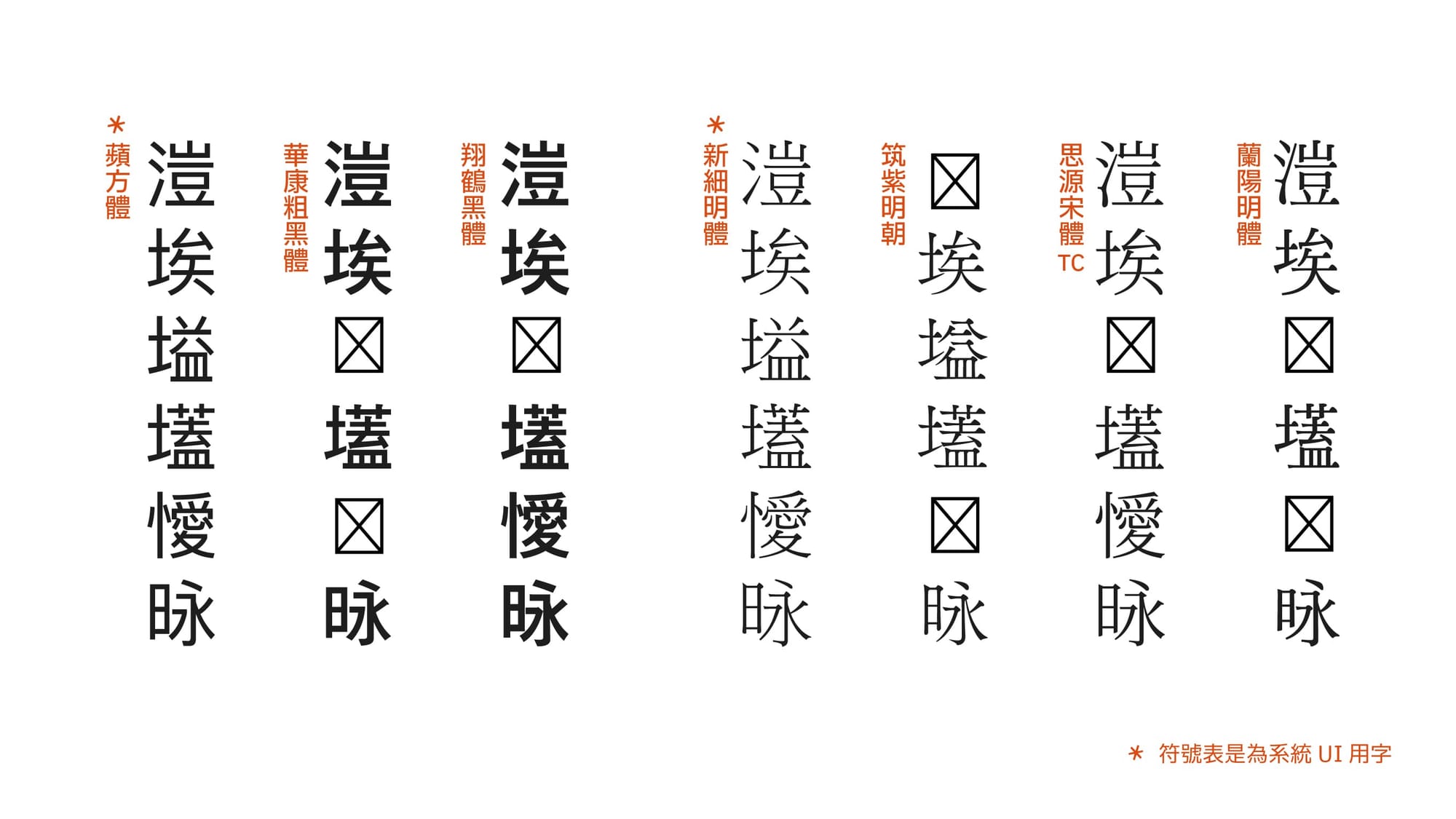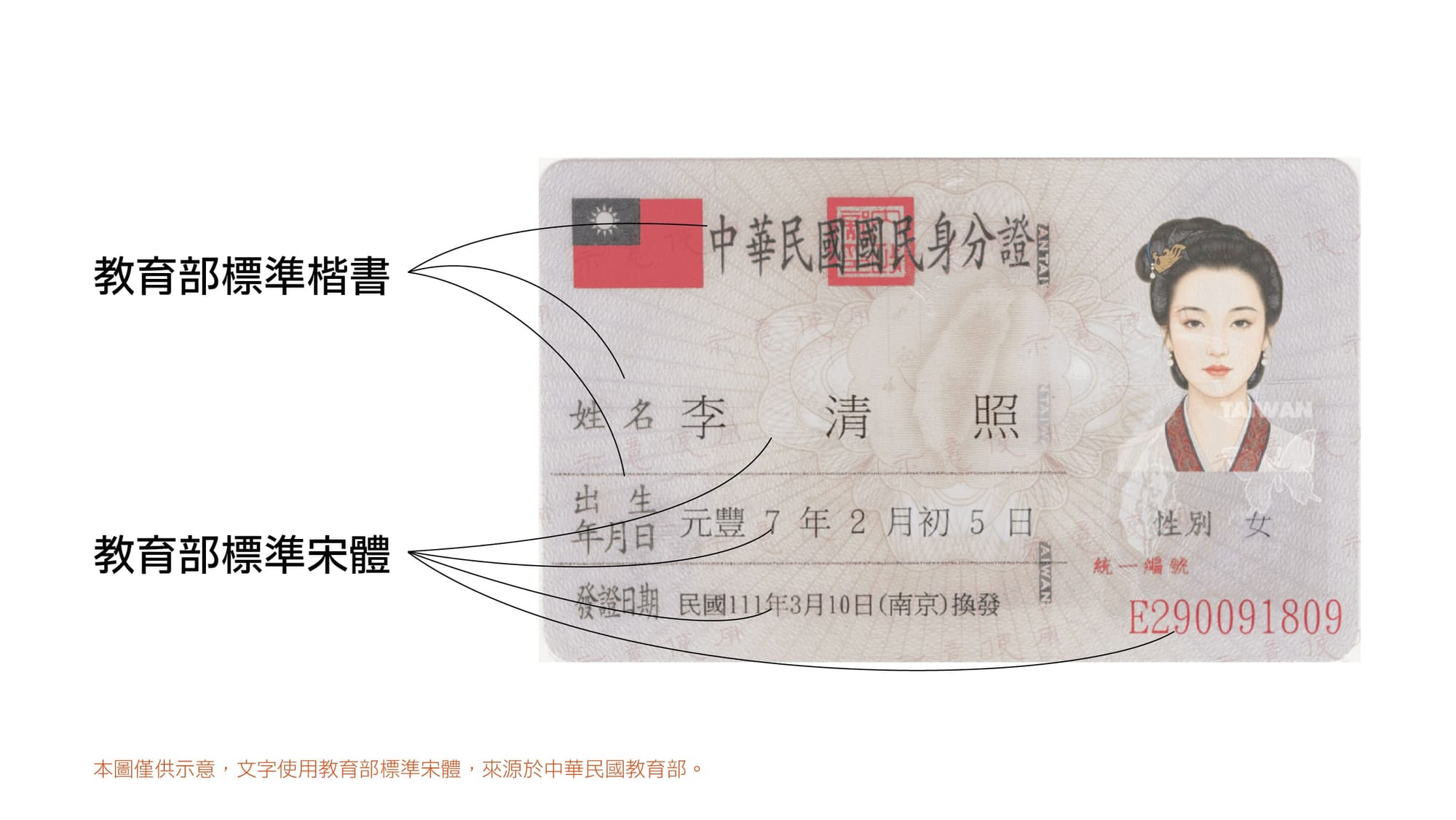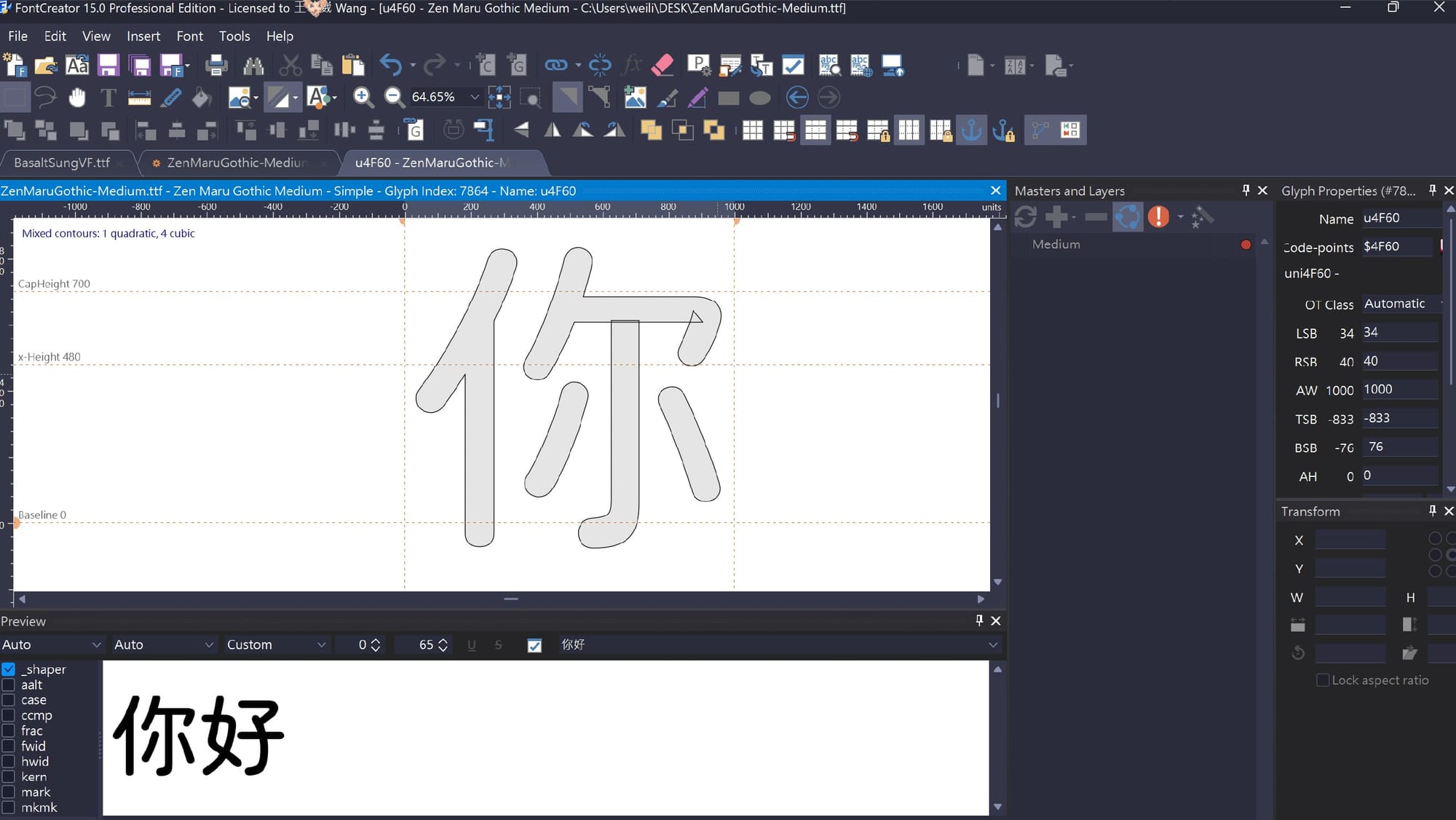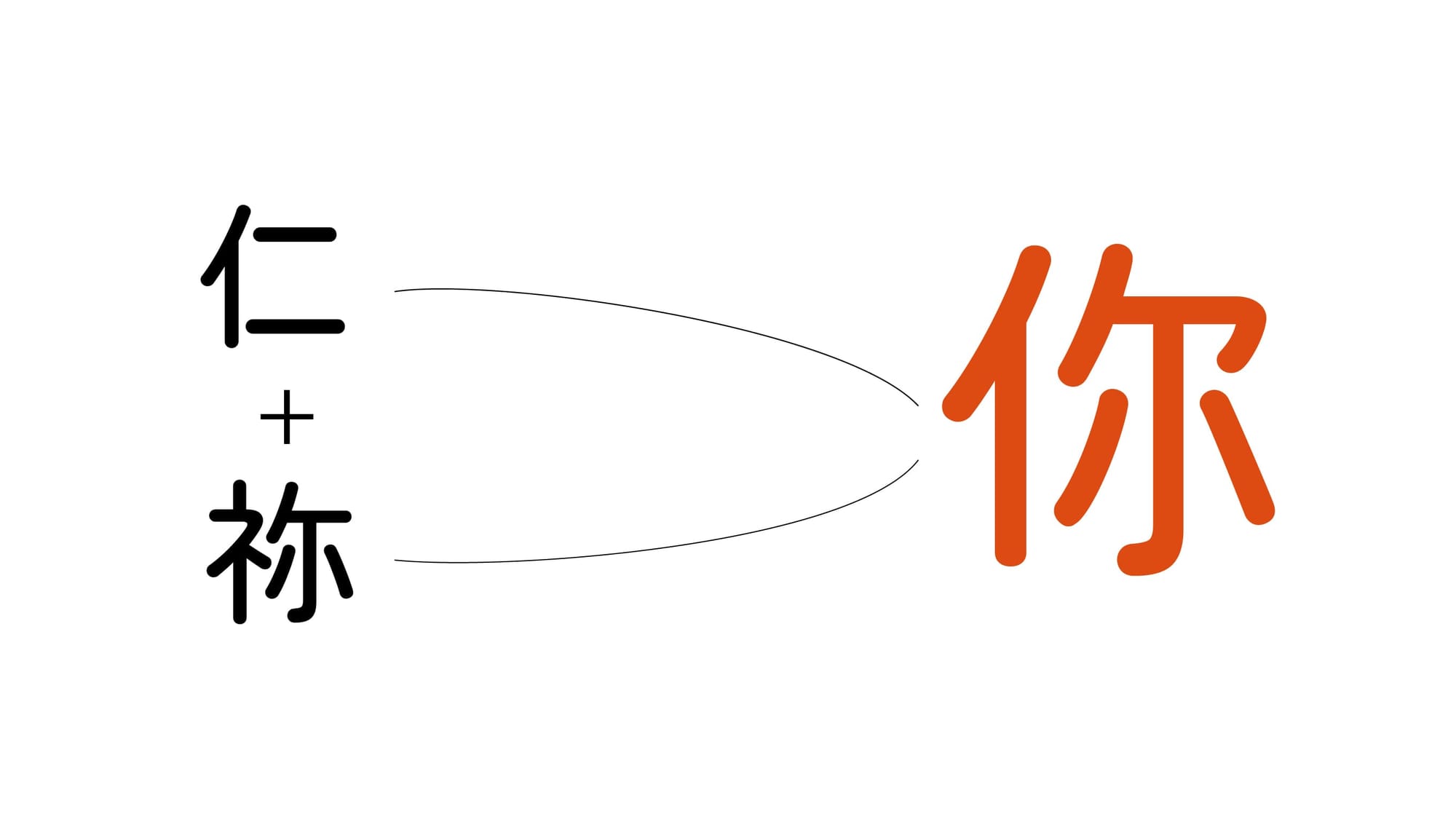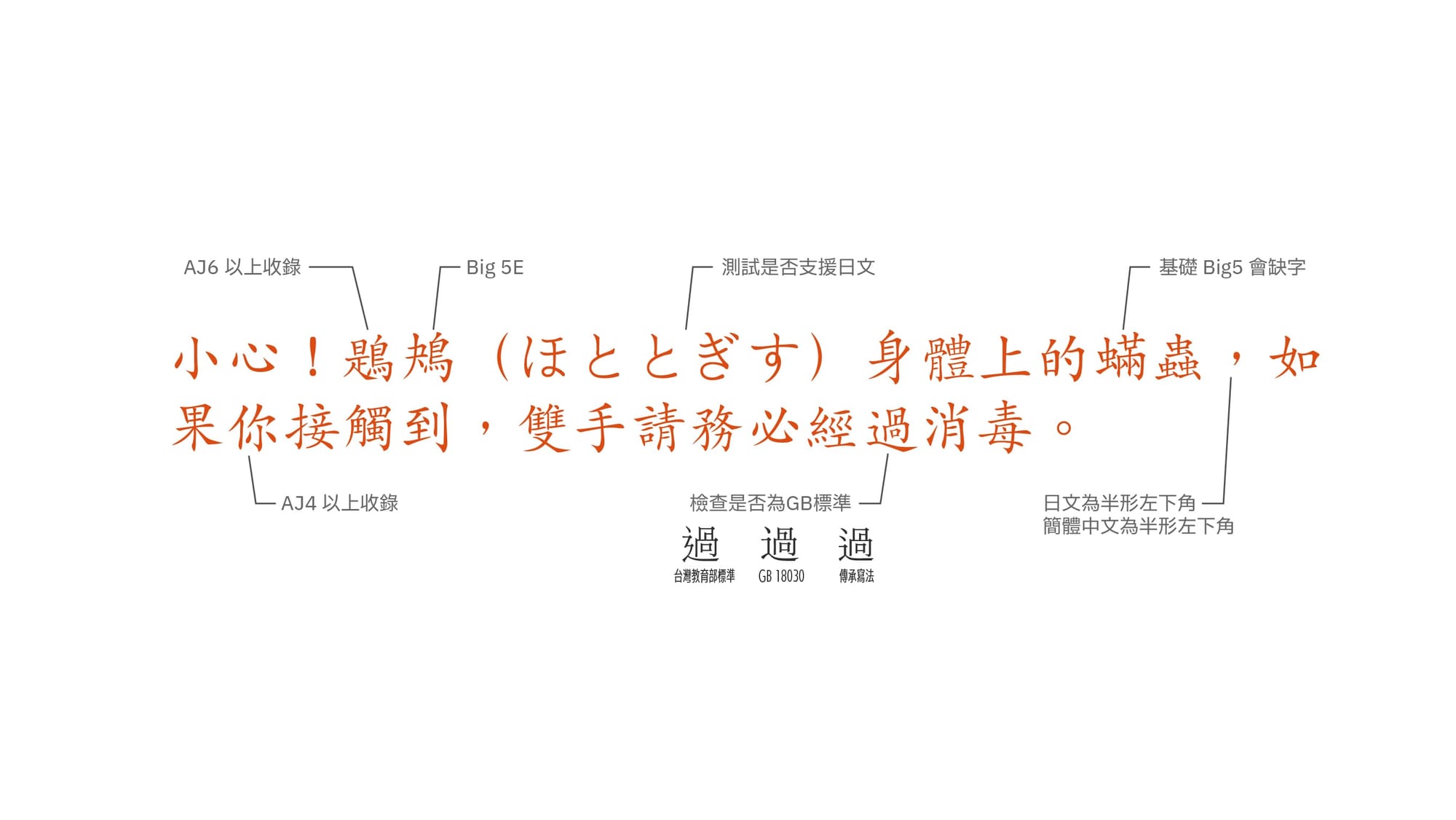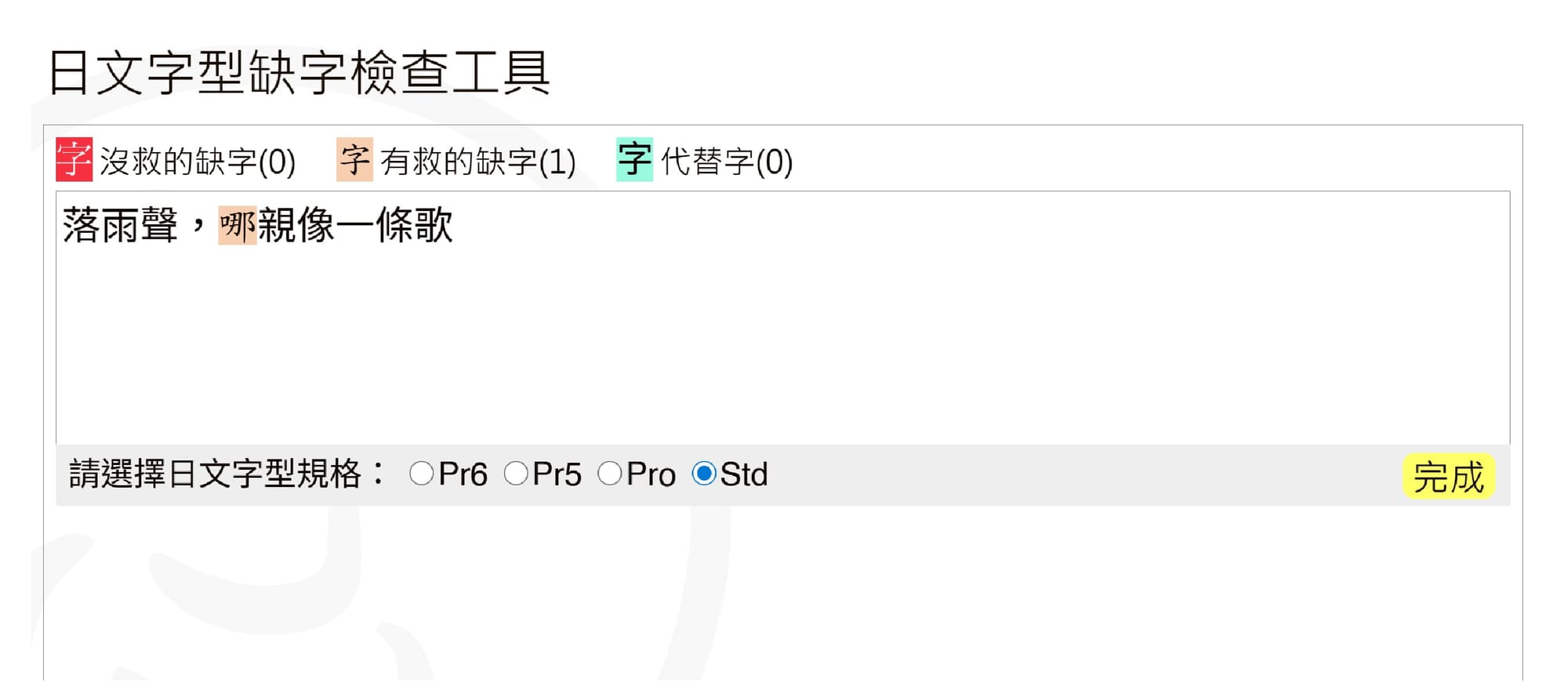
缺字如何解決?
上次我們講到了「為何缺字」,今天要來介紹遇到缺字時的幾個方式!今天分享幾個常見的解決方法!
第一招:換字體
三十六計,走為上策。這聽起來看似投降,但實則最為保險,例如:是要製作大量姓名、教學文件內文,有大量生僻字。強烈建議使用:蘋方...等系統內建字型,或是思源、花園明朝體等字符集相較完整之字體。
個字體對於生僻字顯示狀況示意,包括:蘋方體、華康粗黑體、翔鶴黑體、新細明體、筑紫明朝體、思源宋體、蘭陽明體
系統字型與其他字型對比
這樣的做法在醫院系統、身分證件......等,長出現生僻字之場景十分常見,像是身分證上就採用了「教育部標準宋體」,一款「新細明體」的胞弟字體,雖說在美感上較於基礎,但收錄字數廣,共有 24,034 個字符,適合用於顯示姓名。
中華民國身分證使用字體示意圖
身分證示意圖。
第二招:補字
在少數情況下,可透過補字將缺少的字符,重新封狀進入字體檔案,這樣的方式適合針對開源字體,非常實用,不過前提是,需要擁有字體編輯軟體,像是免費的:FontForge,或是Glyphs、FontCreator等。
以FontCreator為例進行補字畫面節圖
以FontCreator為例進行補字
補字時的技巧是,先觀察相似部件的字符、中宮,在從相似的部件複製,並加以修改。同時已可以參考相似風格的字「形」處理,包括筆畫、筆型風格......等。
組字示意圖,使用Zen Maru Gothic中的「仁」+「祢」組出「你」
以Zen Maru Gothic為例進行補字
此處使用Zen Maru Gothic進行補字作業,因為該字體為日文字形,缺少「你」,因此抓取「祢」與「仁」拼湊後微調。
第三招:日文漢字
此招適用於日文字型,首先我們能先使用「小心!鶗鴂(ほととぎす)身體上的蟎蟲,如果你接觸到,雙手請務必經過消毒。」測試,該字體缺字程度與相關資訊。
測試語句可以檢測字體缺字情況
接著我們能使用網路工具——柯志杰先生製作的「字嗨:日文字型缺字檢查工具」,將文本輸入,並選擇對應字集,查看是否有可替代之可能。
字嗨:日文字型缺字檢查工具畫面截圖
例如使用「VDL ペンジェントル B」該Std標準之字體顯示「心愛的無緣的人」,其中「緣」存在替換字符。
「緣」於日文字體中的替換字
唯這樣的作法,通常是用於主視覺或其他等字數較少的情況下,長文本建議還是選用繁體中文字型,確保顯示效果、排版流暢性。
所以該怎麼做?
如果是開源字體,可以考慮自行補字,或是社區提供的衍生版本。如果是是日文字型存在替換字符的可能性。但如果是大量繁體中文字體缺少,簡易改換成字符集足夠、完整的字體以利後續作業!